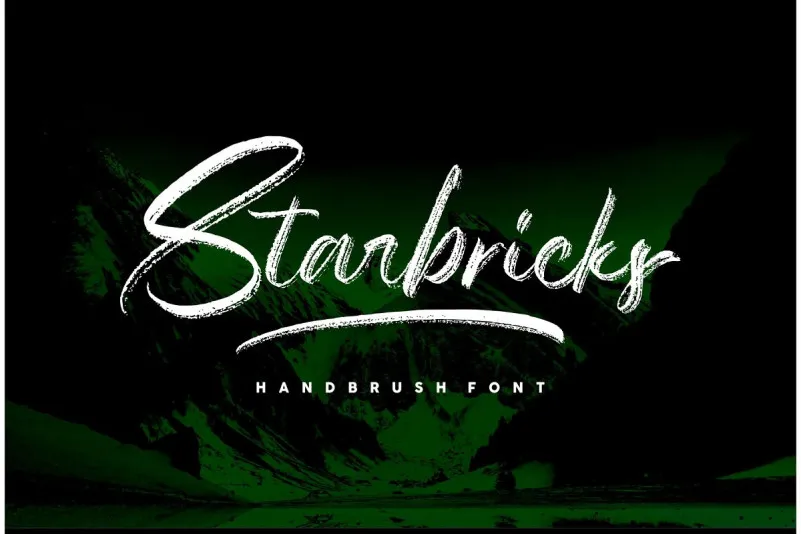
Aqui está uma descrição em português para a página de download da fonte ‘Starbricks Handbrush Font’, adaptada ao tom informativo e convidativo: Esta é uma fonte script à mão livre, inspirada na arte do desenho manual com pincel. É perfeita para designers, blogueiros e qualquer pessoa que adora a escrita à mão ou o garrancho elegante. O design de Starbricks Handbrush Font usa pincéis naturais para criar uma aparência realista e autêntica. O destaque da fonte é sua singularidade na tecnologia OpenType, que adiciona um valor estético a seus designs. Se você quiser explorar mais ainda, também está incluída a opção de swash – o estilo elegante de escrever em letras ao vivo que torna as suas criações únicas e impressionantes. É uma fonte perfeita para quem busca expressar seu próprio estilo criativo, seja na web ou em impressões. Com esta fonte à mão livre Starbricks Handbrush, você pode adicionar um toque autêntico a qualquer projeto gráfico sem precisar de nenhuma ferramenta especializada – desde Adobe Illustrator até Photoshop e Corel Draw. Starbricks Handbrush é uma fonte natural que traz vida ao seu trabalho. Não hesite em experimentar e mostrar sua versão personalizada para cada projeto!